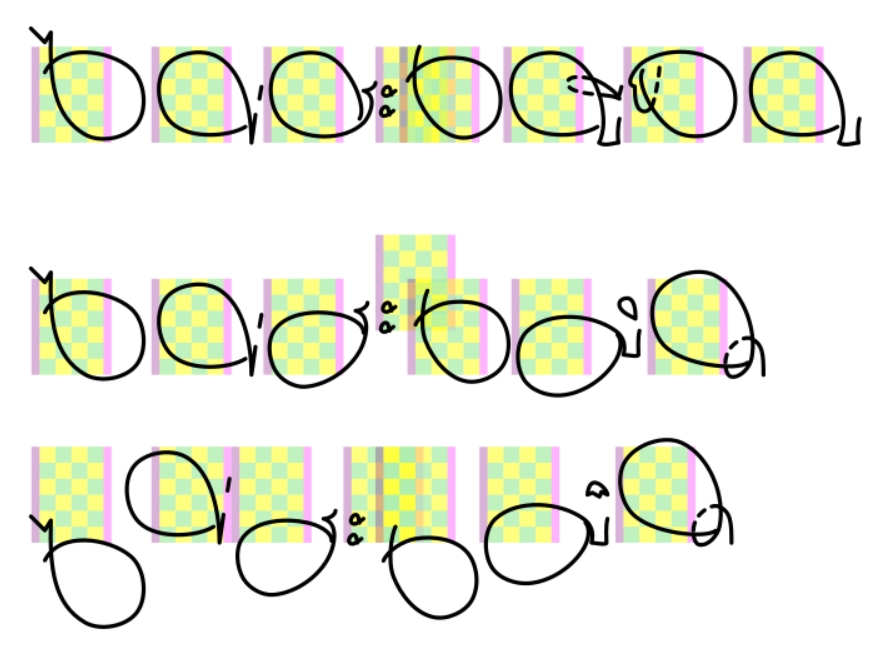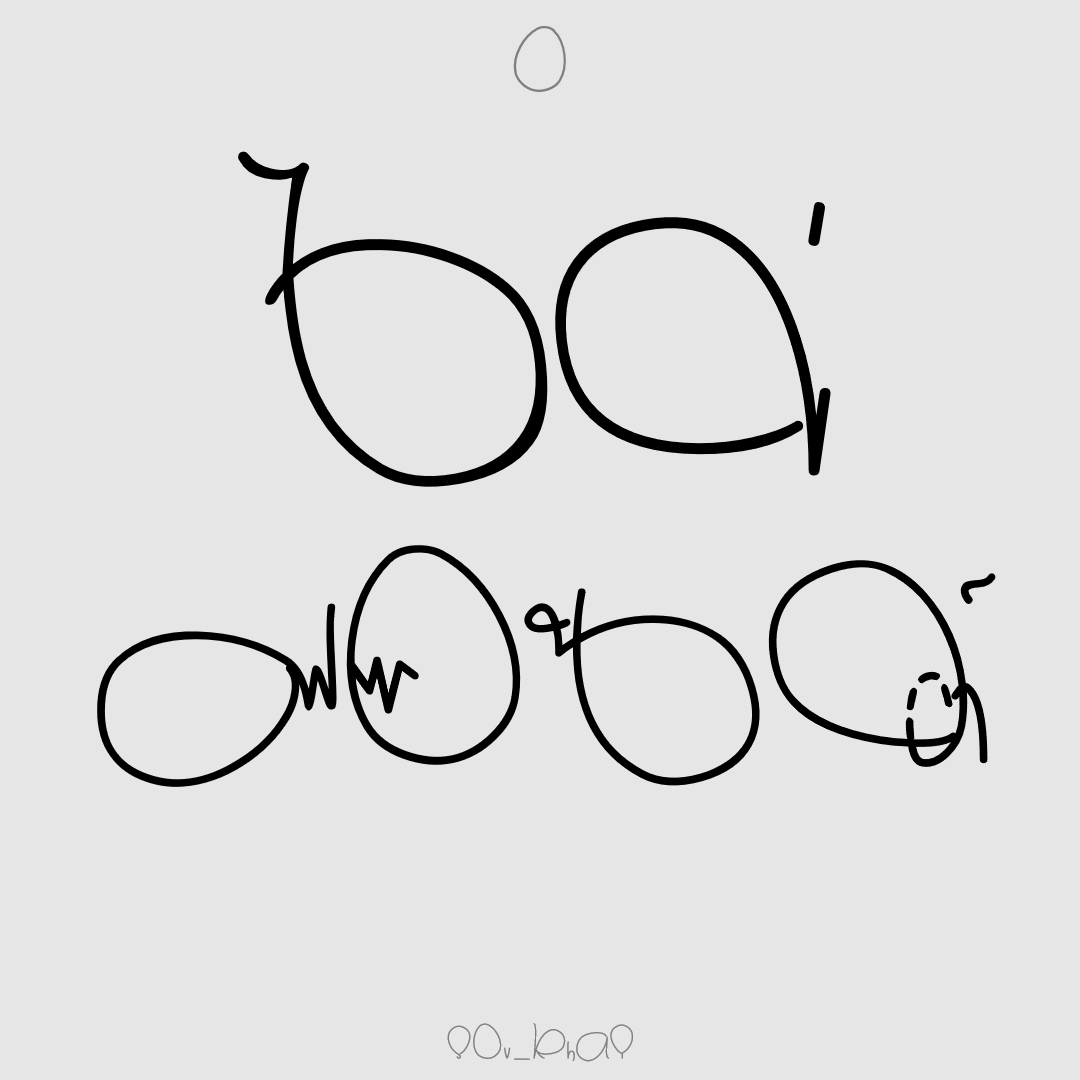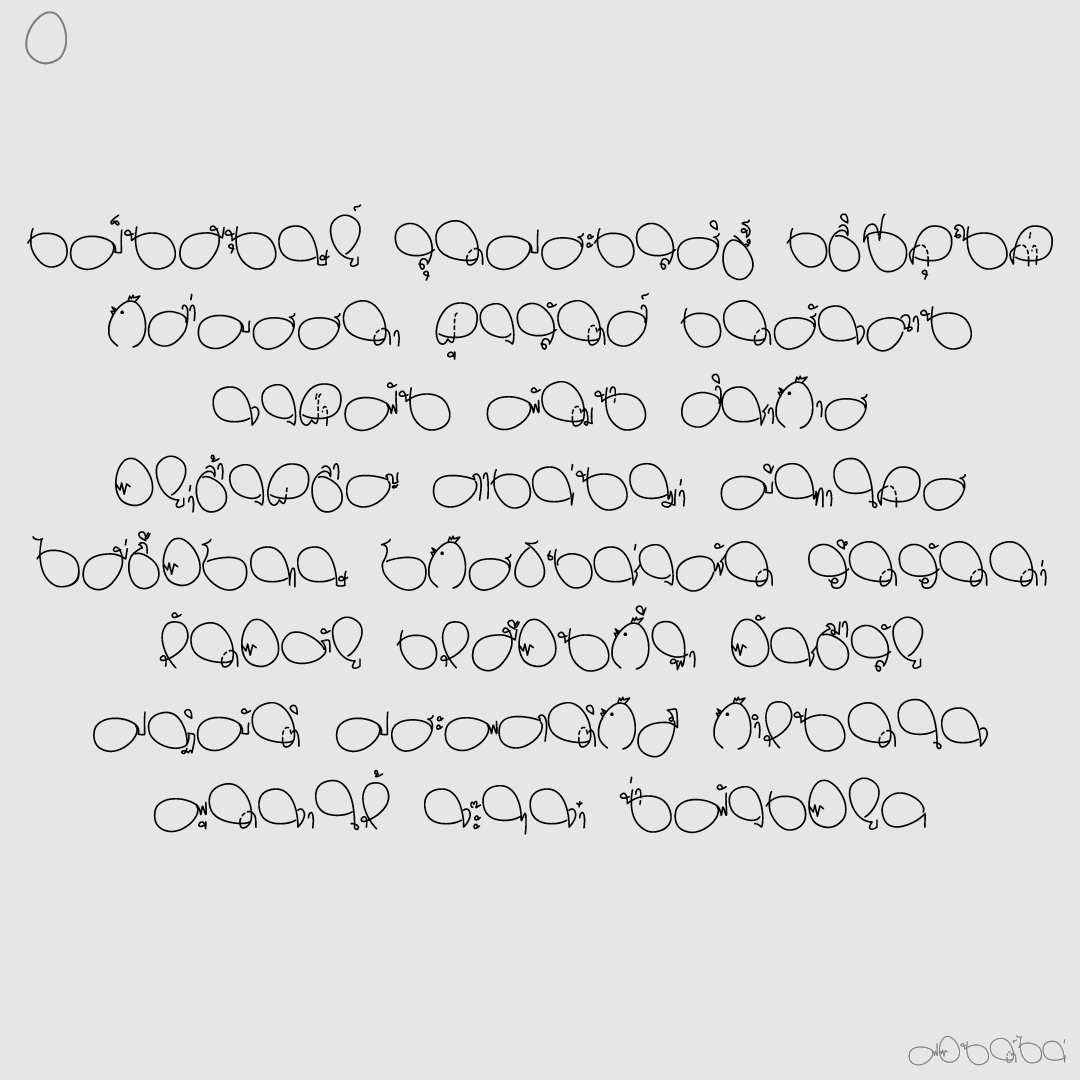
ฟอนต์ ไข่
ฟอนต์ไข่ อักษรหัวขมวดเป็นทรงไข่ ใหญ่กว่าตัวมาก สระอะอา ลอยไปมาได้เหมือนสระอิอี
ปัญหาของหัวโตเกินตัว อยู่ที่พยัญชนะหัวเข้า เช่น ค ด ถ ผ มันทับเส้นหลัง ..แก้ปัญหาด้วย เปลี่ยนเส้นทึบเป็นเส้นประ
อีกปัญหาคือพยัญชนะหัวล่าง ตัวมันลอยขึ้นมา สระอะอา ต้องลอยตามมาด้วย ..แก้ปัญหาด้วย เปลี่ยนไปใช้ระบบ mark แล้วค่อยเพิ่มความกว้างทีหลัง ขึ้นอยู่ว่า สระอะอานั้น ต้องการความกว้างหรือเปล่า
ชื่อฟอนต์ : ไข่
ฟอนต์ไข่ อักษรหัวขมวดเป็นทรงไข่ ใหญ่กว่าขนาดตัวมาก สระอะอา ลอยไปมาได้เหมือนสระอิอี
เนื่องด้วยฟอนต์หัวโต มันอ่านยาก ยิ่งหัวไข่ใหญ่บึ้มยิ่งไม่ต้องพูดถึง  :38:
เดิมที.. กะว่าจะทำให้ ตัวอ่านง่ายอีกตัว เป็น ไข่ระเบียบ(บรรทัดบนสุด) กับ ไข่ระเบิด(บรรทัดกลาง) แต่มันดูไม่ระเบิด เลยทำบรรทัดล่าง ให้ไข่กระจายออกตามแรงระเบิด..อ่านง่ายเฉย!! :40:  --> แต่ว่ามันไม่ต้องการ เทคนิคพิเศษ สระอะอาลอยละล่องไม่ต้องทำกัน :11:  --> เลิกๆ กลับไปทำแบบกลาง คนอ่านหัวระเบิดแทน..ฮี่ๆ :42: